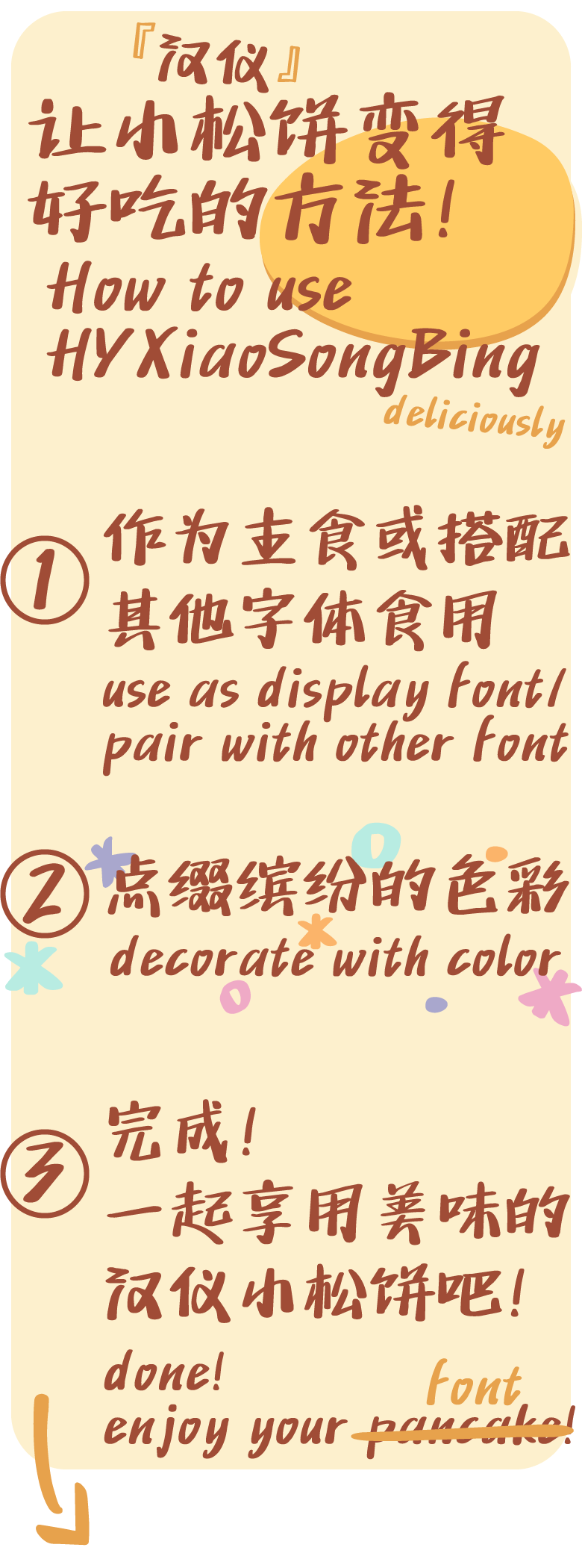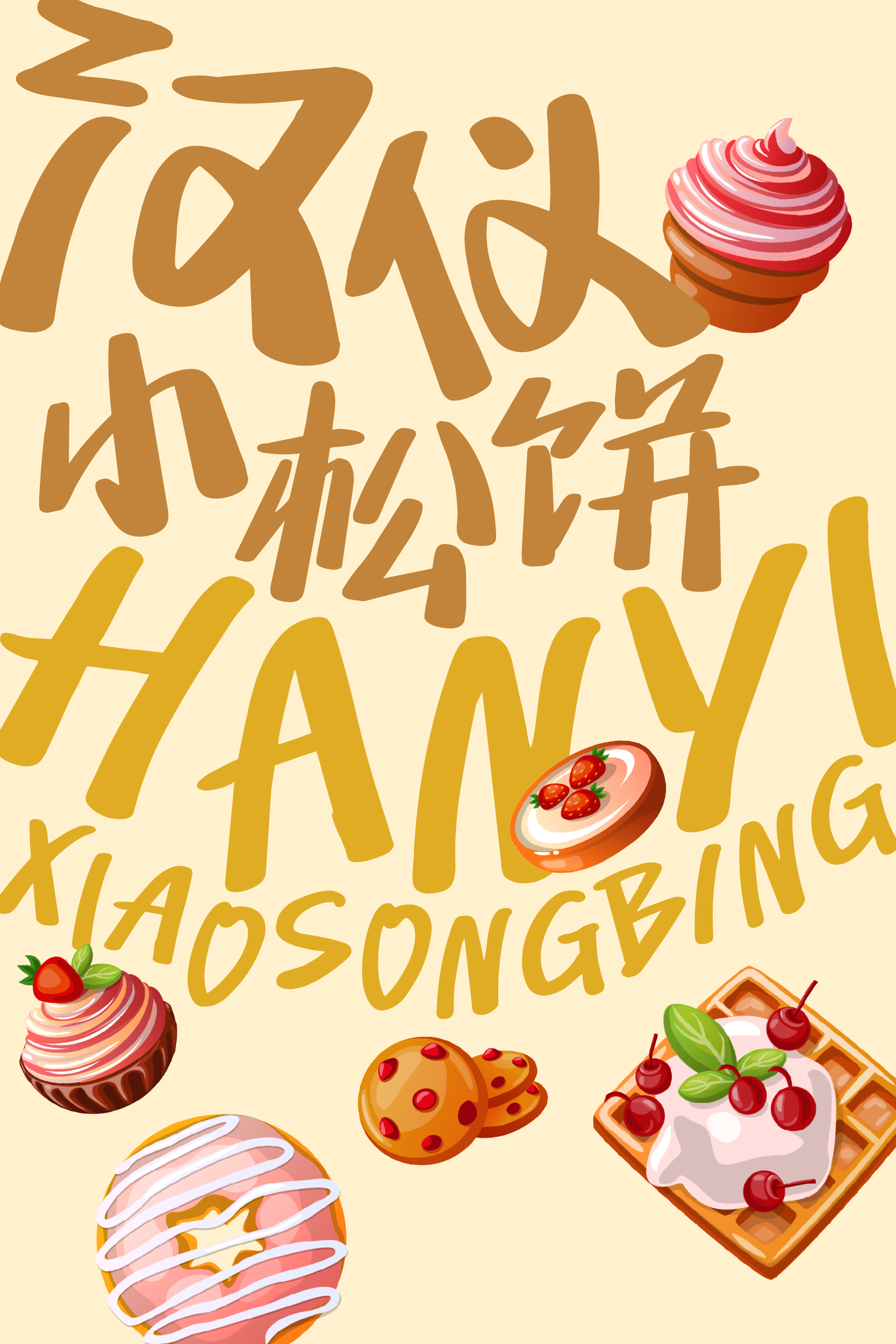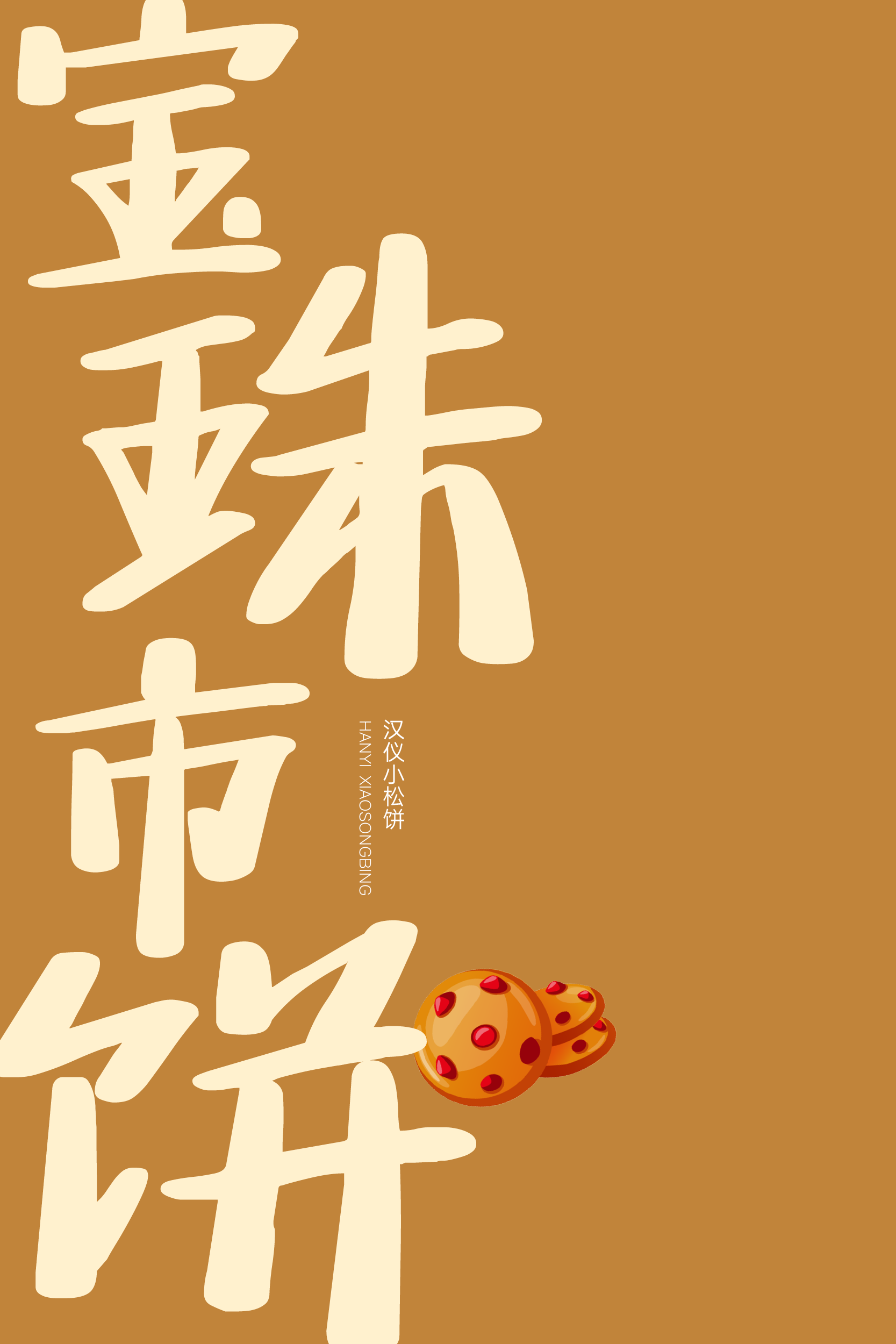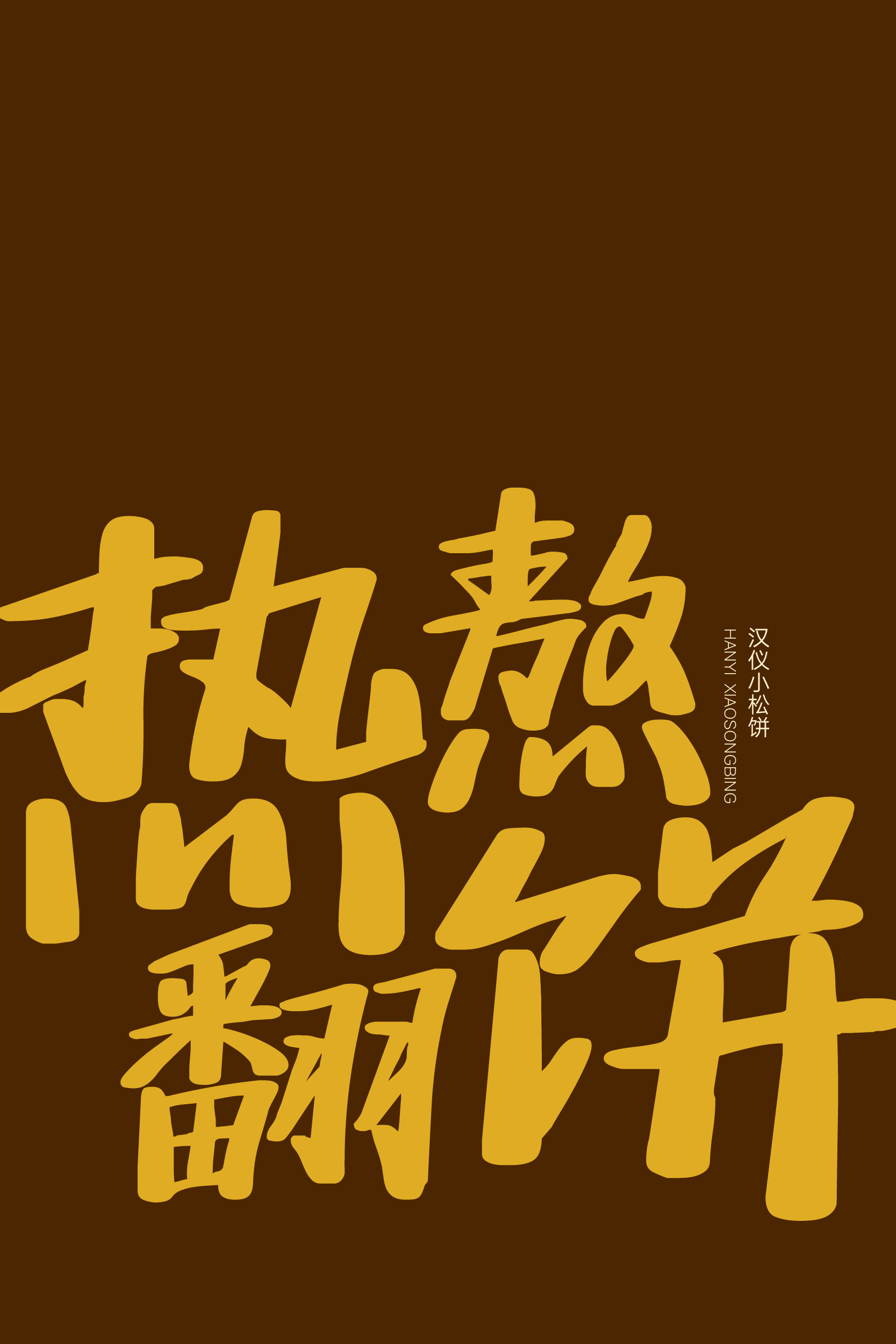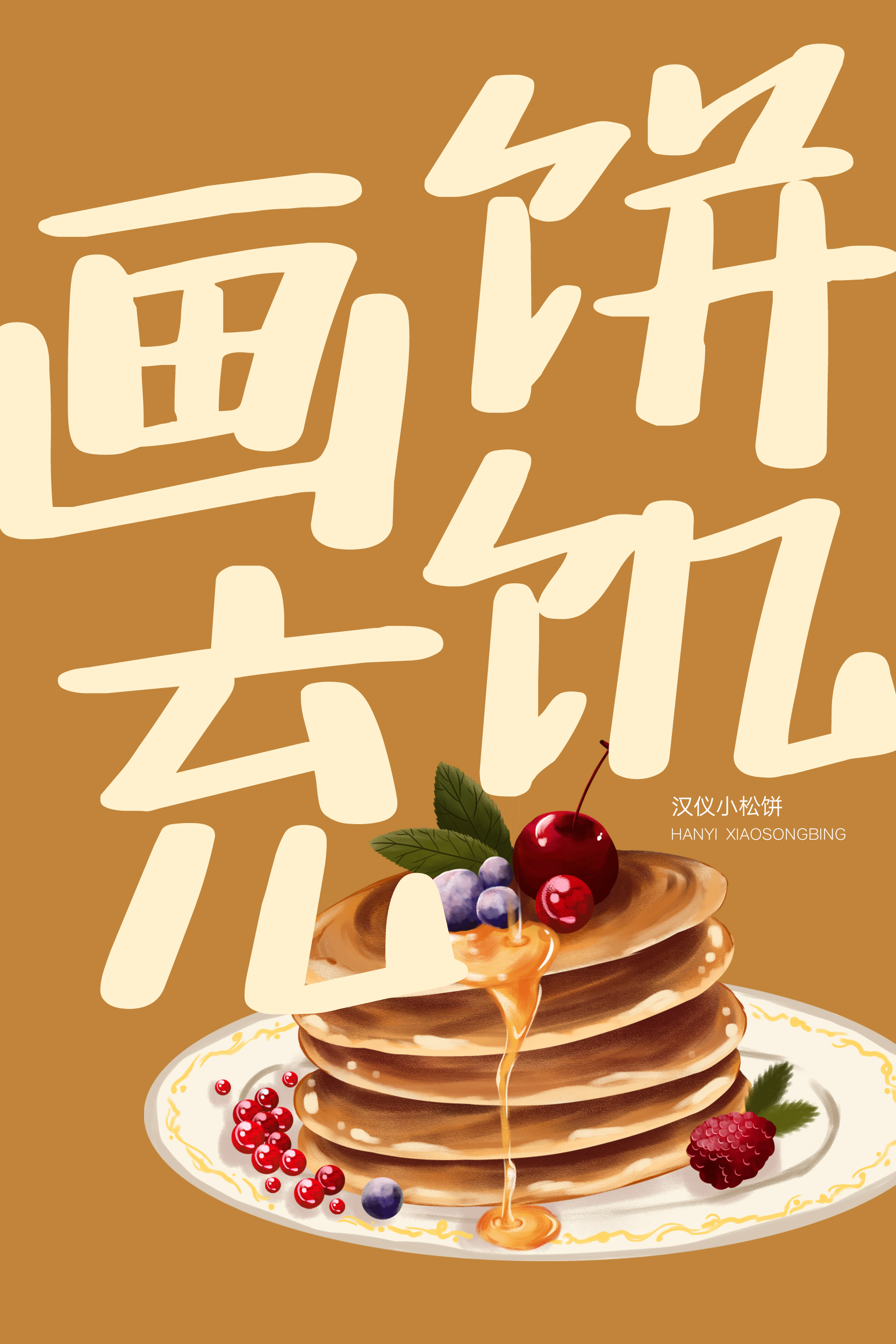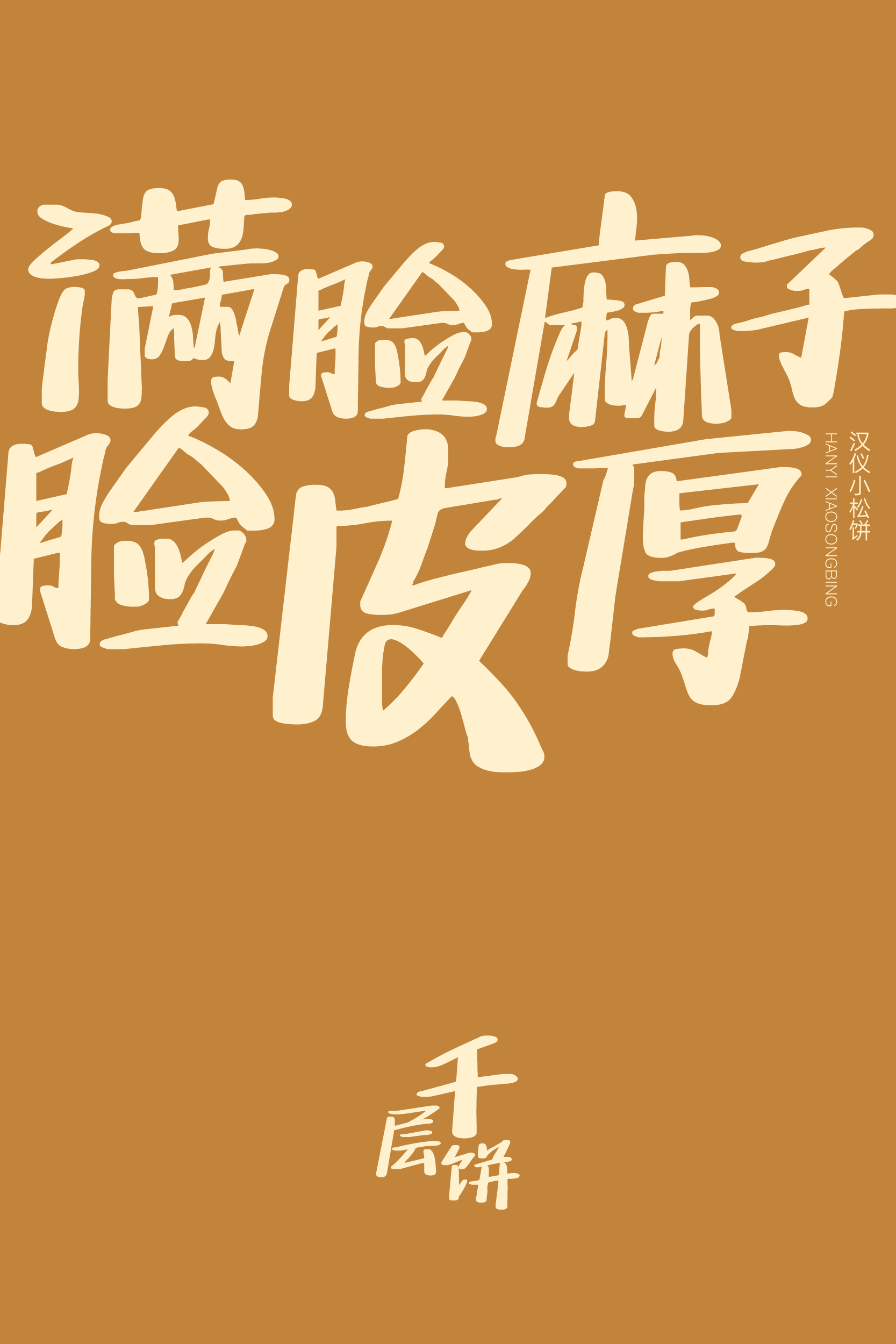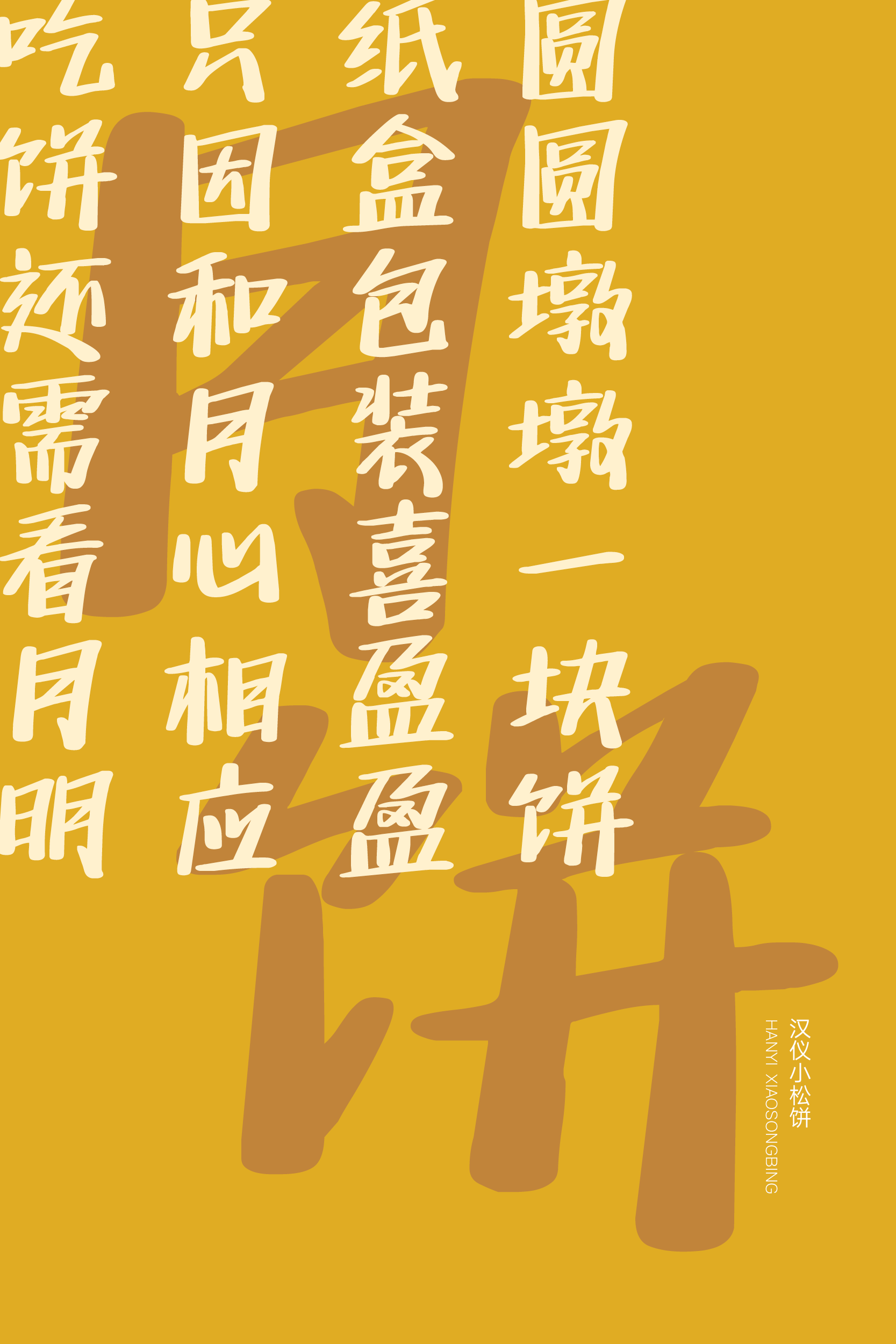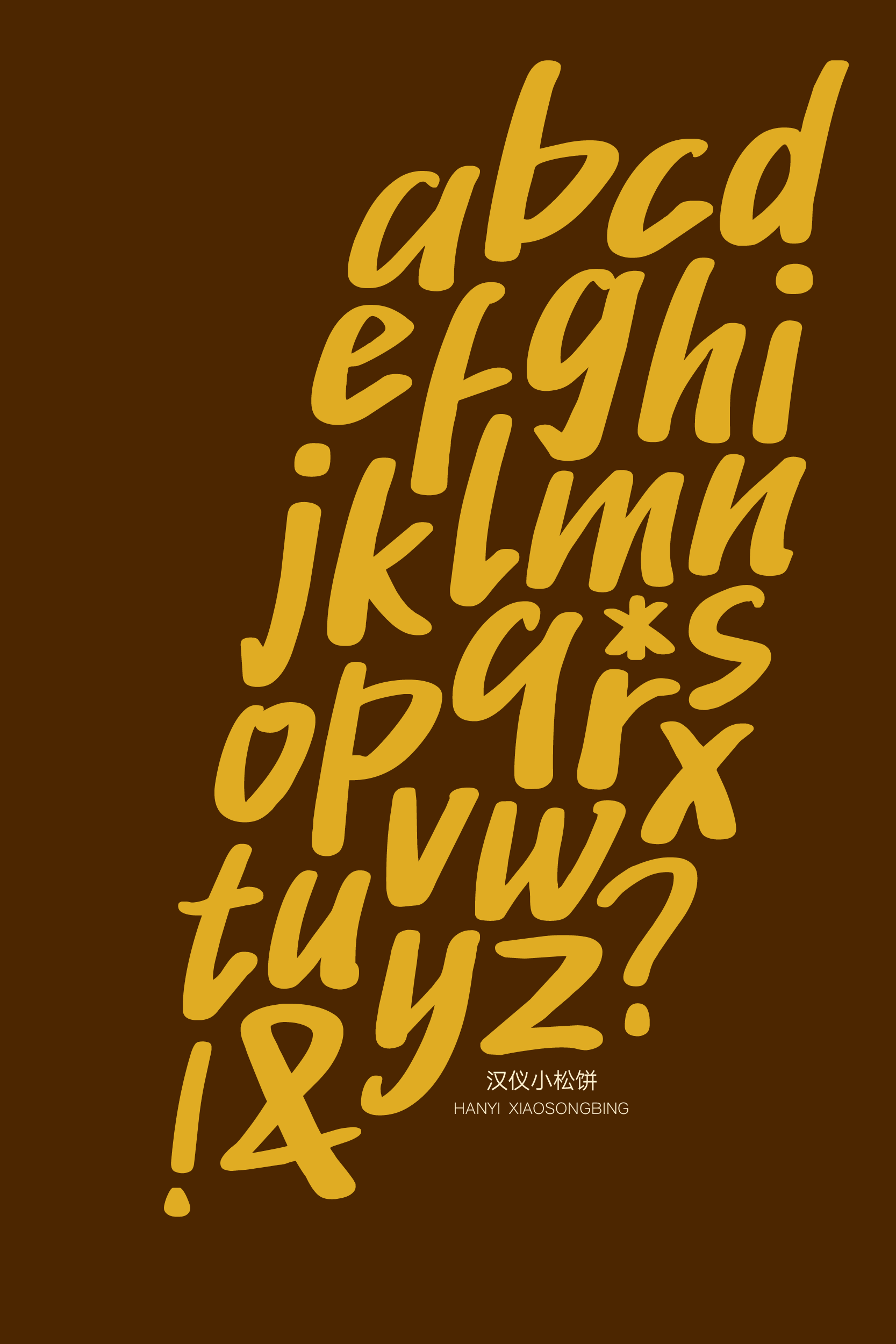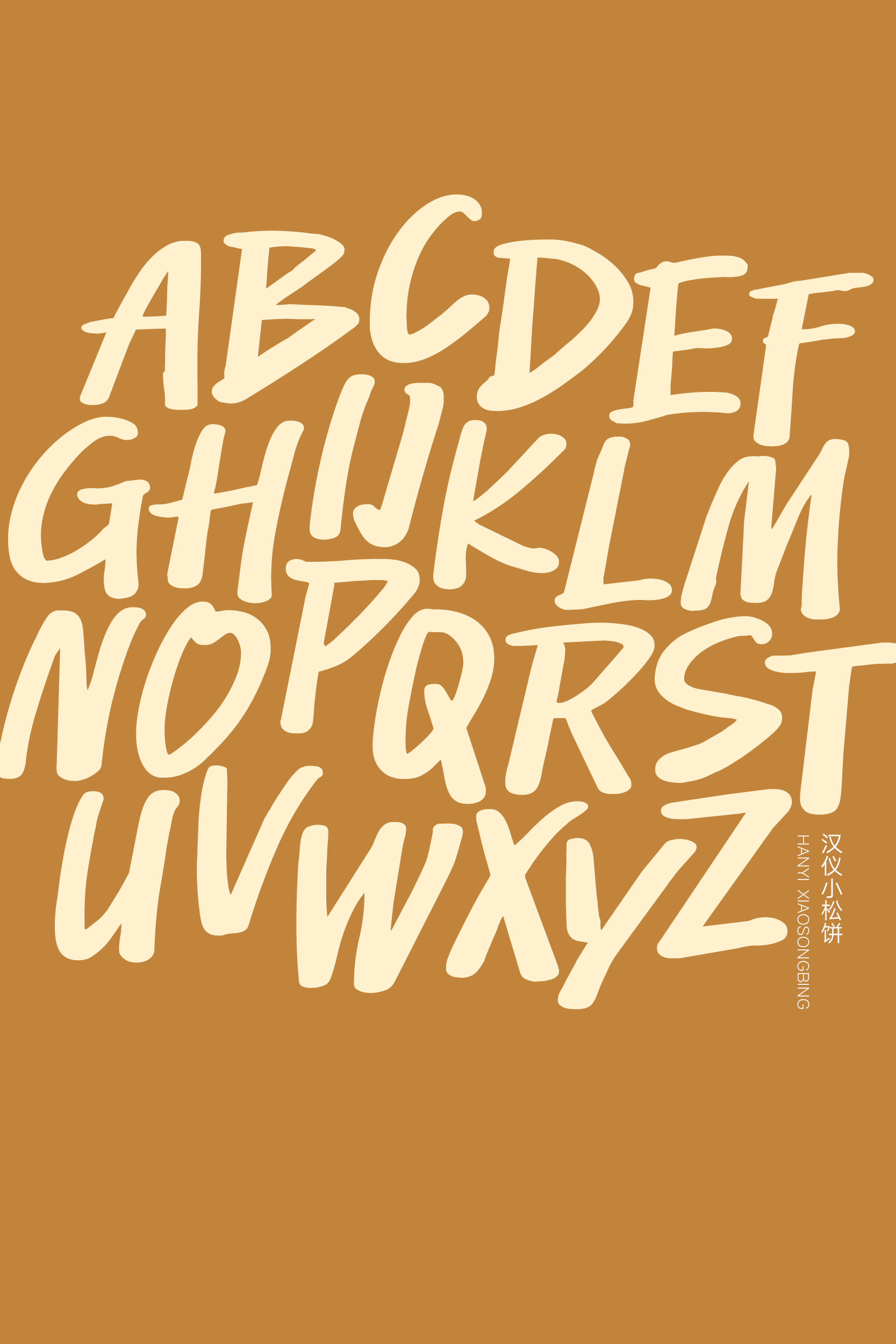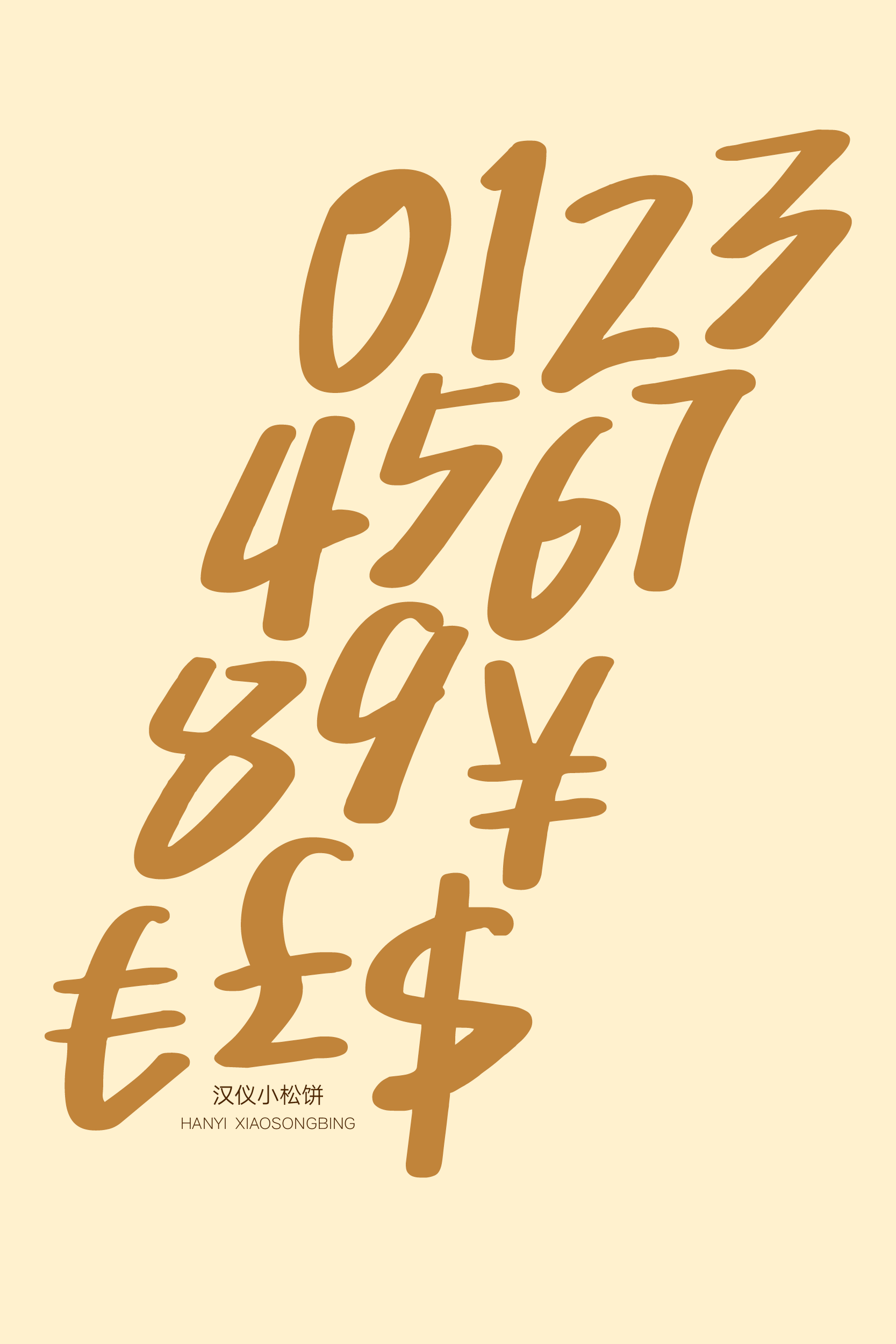
这款字体很美味
汉仪小松饼是由汉仪字库签约作者孙小松创作的一款“好吃”的手写字体,轻松可爱,充满趣味。这款字体如同松饼一般松软可口,如同糖浆一般香甜美味,字形放松,笔画随性,让人在视觉上饱餐一顿。汉仪小松饼适合用于标题字体或较短文本的排版,与美食、休闲、娱乐等场景适配度高,烘托出温馨快乐的氛围。
汉仪小松饼的字形放松,向右上自然倾斜。
随性的笔画和连笔处理就像是淋在松饼上的美味糖浆。
笔画末端的质感如同缓缓滴流的糖浆和黄油,圆润厚重。
汉仪小松饼的西文部分同样是流畅的手写风格,中西文搭配使用和谐舒适。
汉仪小松饼是一款“好吃”的手写字体,适合用于标题字体或者较短文本的排版,运用丰富的色彩与不同字体自由搭配,让好吃的更好吃、好玩的更好玩。